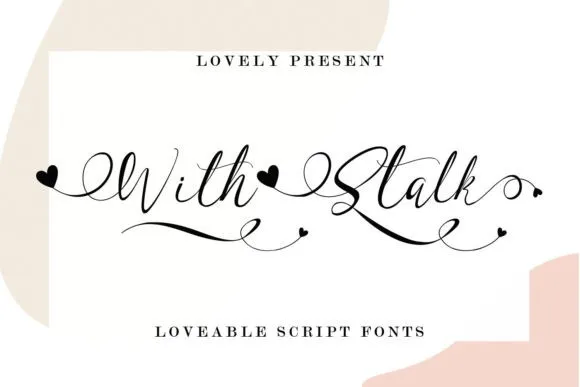
With Stalk Calligraphy Font – Download Grátis
A With Stalk Calligraphy Font é uma opção moderna para adicionar um toque elegante a projetos digitais. Com seu estilo tipográfico de escrita cursiva e muitas alternativas, você tem liberdade para criar texturas únicas e impactantes. Esta fonte foi projetada pela MengulirPena, com uma aparência refinada e fluída que mantém seus influentes desenhos da caligrafia ao mesmo tempo contemporâneos e frescos. É PUA encoded, o que significa que você pode acessar facilmente todos os símbolos e swashes desta fonte de escrita cursiva elegante e fluida. Ela é perfeita para aqueles projetos em que quer dar destaque a um texto específico ou para criar uma atmosfera única e autêntica, levando seus trabalhos ao nível mais alto. Adorarão esse recurso gráfico.